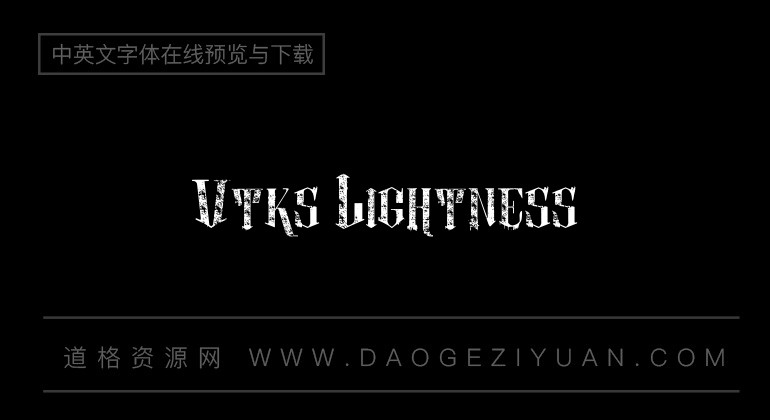
Vtks Lightness 是一种免费的装饰性字体,由巴西的设计师Douglas Vitkauskas创建。这种字体具有极高的可读性和清晰度,并且非常适合用于海报、标志、书籍封面、宣传册、产品包装等设计项目中。 Vtks Lightness 字体的特点是具有鲜明的装饰性,字母形状非常漂亮。然而,它的字母间距相对较小,因此可能不适用于长段落文本。这种字体的设计灵感来自印刷和涂鸦艺术,导致字母的外形轮廓非常有趣,因此非常适合用于视觉设计和创意项目。 Vtks Lightness 字体是一种 TrueType 字体,可以在 Windows 和 Mac OS X 上使用。该字体还有一些变体可供选择,例如 Vtks Lightness 2、Vtks Lightness Shadow、Vtks Lightness Bold 等。内容介绍
Vtks Lightness是一款非常不错的手写艺术字体,具有很好的视觉感,适合于文化类的宣传设计、商业类品牌的广告和产品包装设计以及个性化文字排版等较多场景。